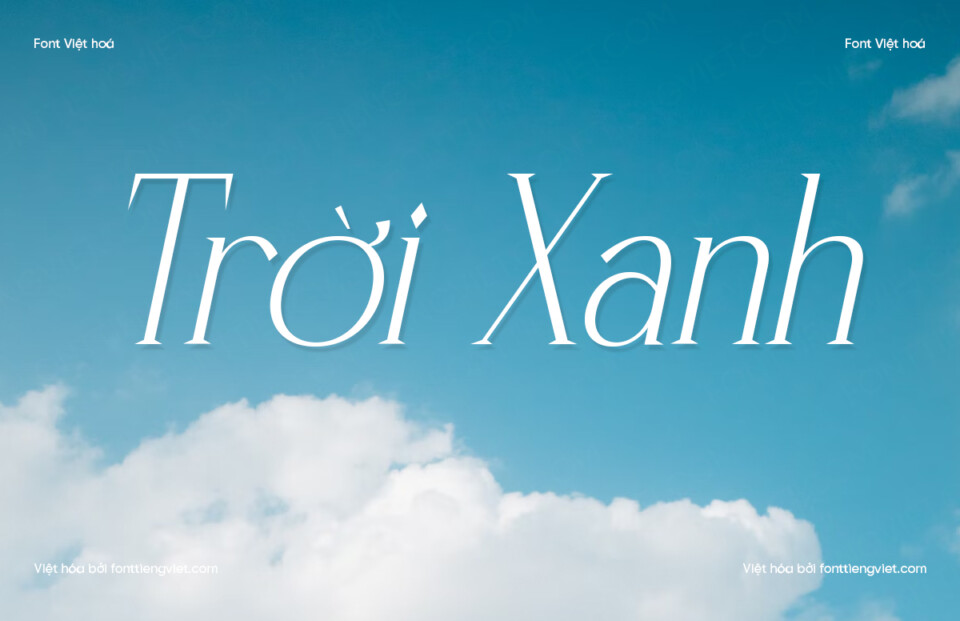
Font Việt hóa 1FTV VIP Qarinthen Italic
Font Việt hóa 1FTV VIP Qarinthen Italic – Đẳng cấp nghệ thuật chữ viết bay bổng
Trong thế giới thiết kế đồ họa hiện đại, việc lựa chọn một bộ Font Miễn Phí chất lượng luôn là ưu tiên hàng đầu của các designer chuyên nghiệp. Một trong những cái tên đang tạo nên cơn sốt trong cộng đồng sáng tạo tại Việt Nam chính là Font Việt hóa 1FTV VIP Qarinthen Italic. Đây không chỉ là một bộ chữ thông thường mà còn là sự kết hợp hoàn hảo giữa nét cổ điển quý phái và tinh thần hiện đại đầy phóng khoáng. Với những đường nét thanh mảnh, uốn lượn tinh tế, bộ font này hứa hẹn sẽ mang đến một làn gió mới cho mọi dự án thiết kế từ đơn giản đến phức tạp, giúp tác phẩm của bạn trở nên nổi bật và thu hút ánh nhìn ngay từ lần đầu tiên.
Sức hút khó cưỡng của Font Việt hóa 1FTV VIP Qarinthen Italic trong thiết kế
Lý do khiến Font Việt hóa 1FTV VIP Qarinthen Italic trở thành lựa chọn hàng đầu của nhiều nhà thiết kế chính là cấu trúc chữ nghiêng (Italic) vô cùng đặc biệt. Không giống như các phông chữ nghiêng thông thường vốn chỉ tập trung vào độ dốc, Qarinthen Italic chú trọng vào nhịp điệu và sự cân đối giữa các ký tự. Mỗi chữ cái được chăm chút tỉ mỉ với những nét móc bay bổng, tạo cảm giác như những nét bút lông uyển chuyển trên mặt giấy cao cấp. Điều này đặc biệt phù hợp với các dự án đòi hỏi tính thẩm mỹ cao và sự sang trọng tuyệt đối.
Ứng dụng đa dạng trong nhiều lĩnh vực sáng tạo
Bộ Font Việt hóa 1FTV VIP Qarinthen Italic sở hữu khả năng ứng dụng cực kỳ linh hoạt. Bạn có thể dễ dàng bắt gặp bộ font này trên các thiệp mời đám cưới sang trọng, bìa sách nghệ thuật, hay các ấn phẩm quảng cáo cho các nhãn hàng thời trang và mỹ phẩm cao cấp. Ngoài ra, trong lĩnh vực thiết kế logo và nhận diện thương hiệu, Qarinthen Italic giúp truyền tải thông điệp về sự tinh tế, chuyên nghiệp và đẳng cấp. Đặc biệt, việc được Việt hóa kỹ lưỡng bởi đội ngũ 1FTV giúp font chữ này hiển thị mượt mà, không gặp lỗi dấu tiếng Việt, đảm bảo tính thẩm mỹ đồng nhất cho toàn bộ văn bản.
Ưu điểm vượt trội khi sử dụng Font Việt hóa 1FTV VIP Qarinthen Italic
Bên cạnh vẻ đẹp ngoại hình, Font Việt hóa 1FTV VIP Qarinthen Italic còn ghi điểm nhờ sự ổn định trong hiển thị kỹ thuật số. Font chữ này đã được tối ưu hóa để hoạt động tốt trên cả các phần mềm thiết kế chuyên dụng như Adobe Photoshop, Illustrator cho đến các ứng dụng văn phòng cơ bản. Độ sắc nét của các nét mảnh được giữ vững ngay cả khi bạn phóng to hoặc thu nhỏ kích thước, giúp bản in luôn đạt chất lượng cao nhất. Hơn nữa, phong cách Italic đặc trưng của nó còn giúp tạo điểm nhấn mạnh mẽ cho các tiêu đề hoặc các đoạn trích dẫn quan trọng, làm cho bố cục thiết kế trở nên có chiều sâu và sinh động hơn bao giờ hết.
Lưu ý khi phối hợp font chữ trong dự án
Để phát huy tối đa vẻ đẹp của Font Việt hóa 1FTV VIP Qarinthen Italic, bạn nên kết hợp nó với những font chữ không chân (Sans Serif) đơn giản và hiện đại. Sự tương phản giữa những đường nét uốn lượn của Qarinthen và sự cứng cáp của font bổ trợ sẽ tạo nên một tổng thể hài hòa và chuyên nghiệp. Đừng ngần ngại sử dụng các khoảng trắng rộng rãi để bộ font này có “không gian thở”, giúp người xem dễ dàng cảm nhận được sự tinh tế trong từng nét chữ. Đây chính là bí quyết để tạo nên những tác phẩm thiết kế mang đậm dấu ấn cá nhân và tầm vóc quốc tế.
Kết luận về bộ chữ Qarinthen Italic đẳng cấp
Tóm lại, Font Việt hóa 1FTV VIP Qarinthen Italic là một công cụ đắc lực không thể thiếu trong kho tài nguyên của bất kỳ ai yêu thích cái đẹp. Với sự hỗ trợ tận tình từ cộng đồng Font Miễn Phí, Font Việt Hóa, Font Việt hóa 1FTV VIP Qarinthen Italic, việc tiếp cận và sử dụng những bộ font chất lượng cao chưa bao giờ dễ dàng đến thế. Hãy để sự sáng tạo của bạn bay xa cùng những nét chữ tuyệt mỹ này, biến những ý tưởng sơ khai thành những tác phẩm nghệ thuật đích thực. Chúc bạn có những trải nghiệm thiết kế tuyệt vời và thành công rực rỡ với sự lựa chọn tinh tế này cho các dự án sắp tới của mình.